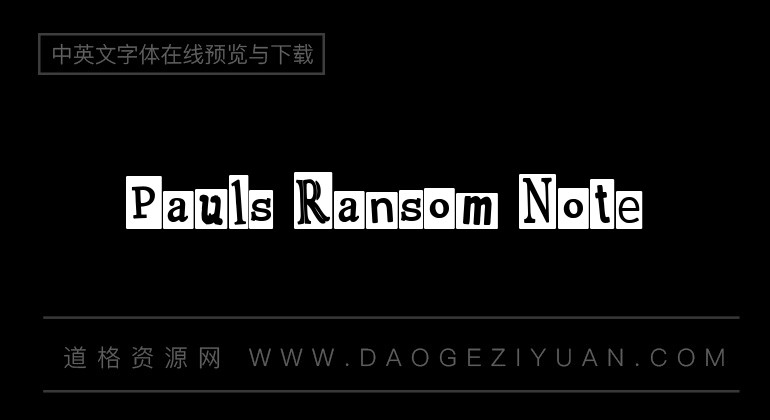
Pauls Ransom Note是一款卡通类型的字体,由Paulsfonts设计,于2018年发布。它具有非常独特的设计,带有一种活泼的气息,可以让您的文字看起来更有趣。Pauls Ransom Note字体的字体细节十分精致,可以带来明亮的视觉效果,并且可以轻松地与其他字体搭配使用。它可以用于商业广告、T恤、海报、卡片等多种用途,可以让您的内容看起来更有趣,更加吸引人。内容介绍
Pauls Ransom Note是一款非常不错的手写艺术字体,具有很好的视觉感,适合于文化类的宣传设计、商业类品牌的广告和产品包装设计以及个性化文字排版等较多场景。